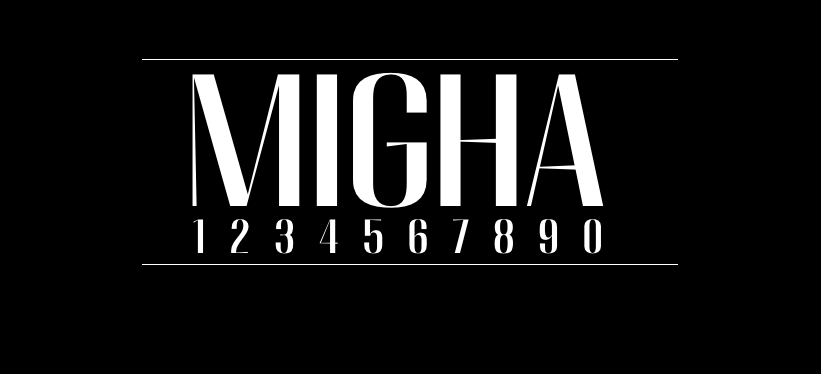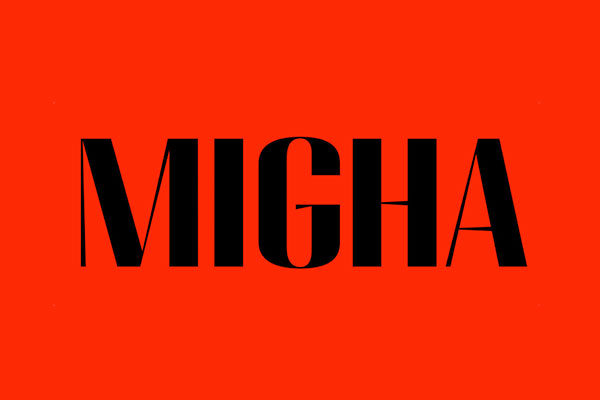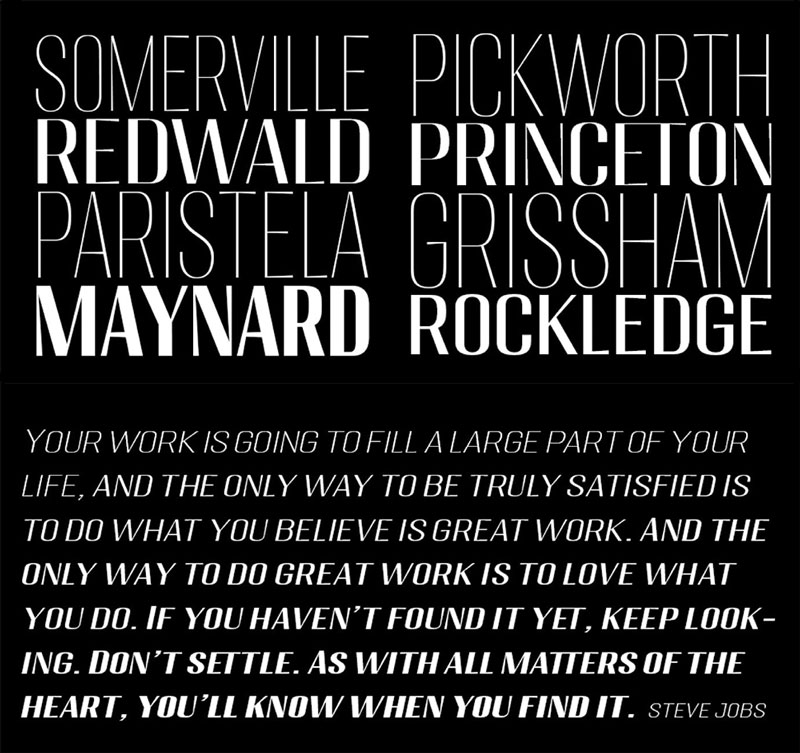
MIGHA
MIGHA是Seniors Studio推出的一款免费英文字体,该显示字体家族设计具有现代和复古感。适用于任何品牌,杂志,海报,徽标,标题,博客等。它带有一整套大写字母,数字,标点符号和多语言支持。
值得一提的是,该字体家族包含了非常多的字重,以及笔画粗细的调节,因此整个压缩包包含了惊人的96个字体文件,各种斜体、粗体、细体应有尽有。